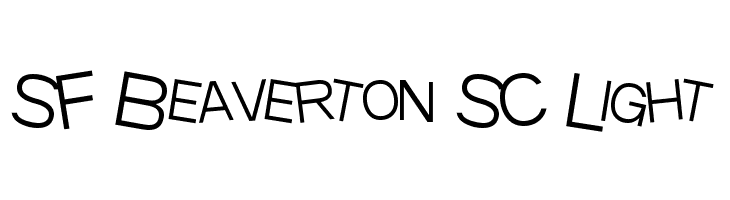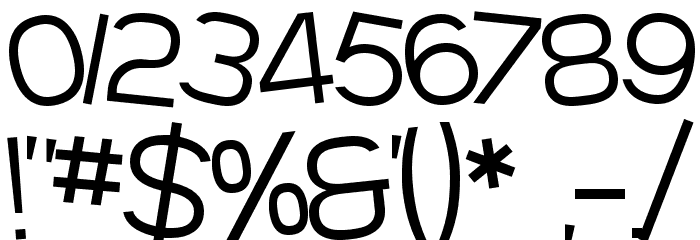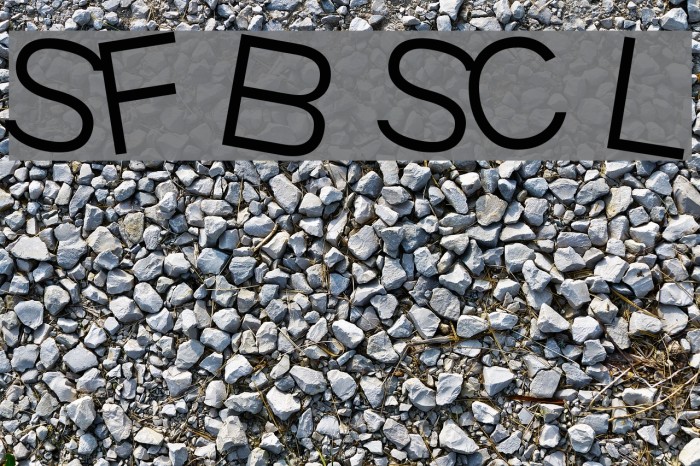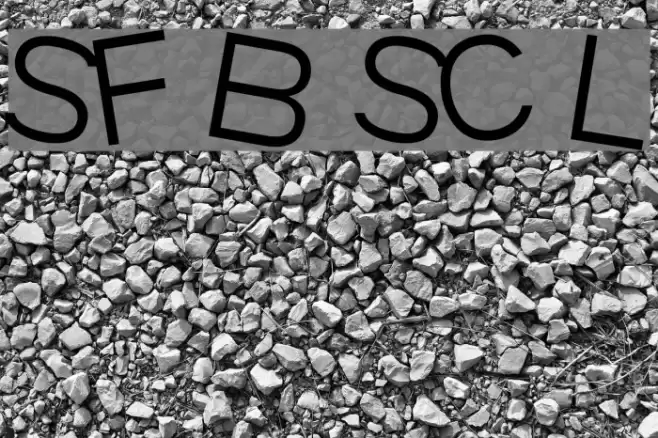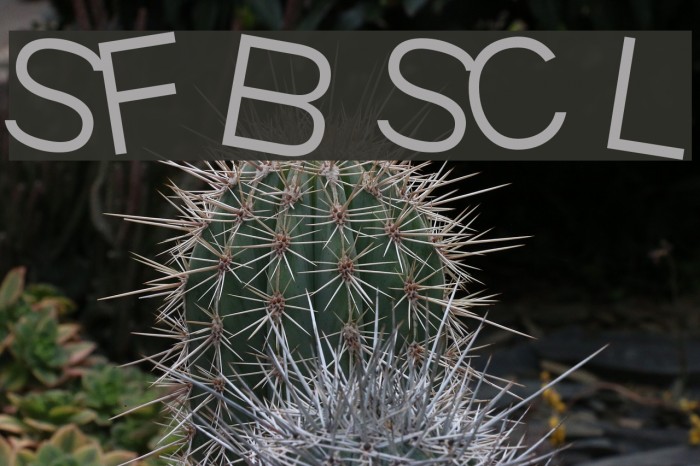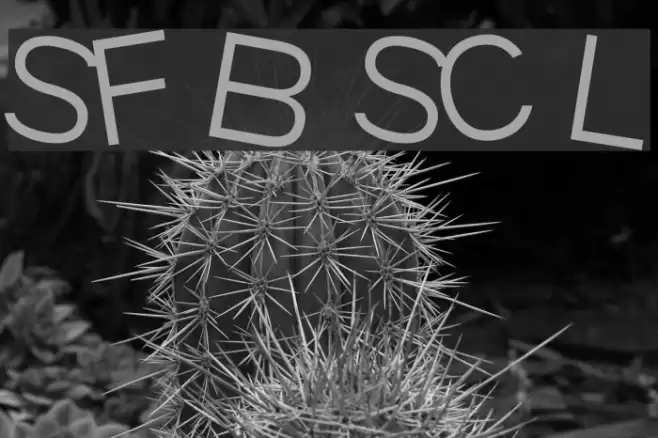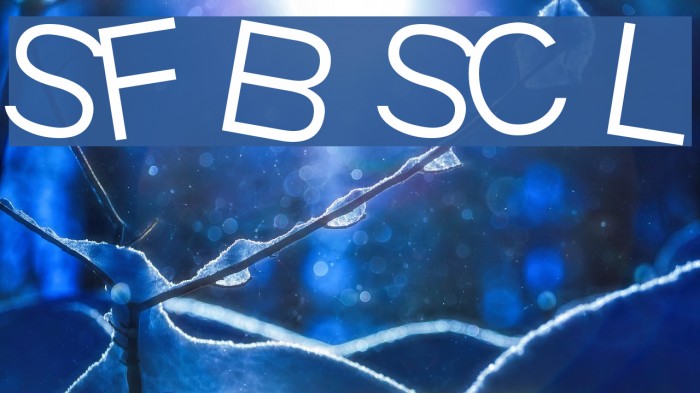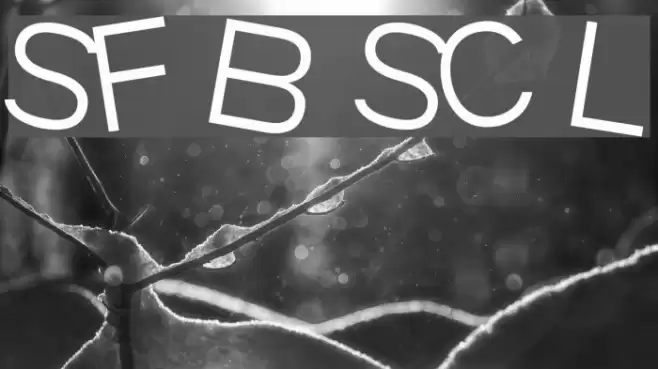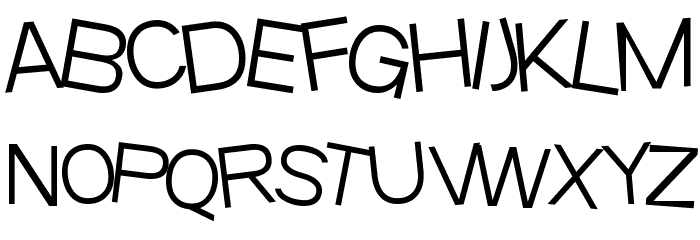
SF Beaverton SC Light Font
✎ Old fashioned
| Peso | Light |
| Categorias | Old fashioned |
| Estilo geral | Playful, Whimsical |
| Projetos propostos | Children's books, playful branding, creative posters, informal invitations. |